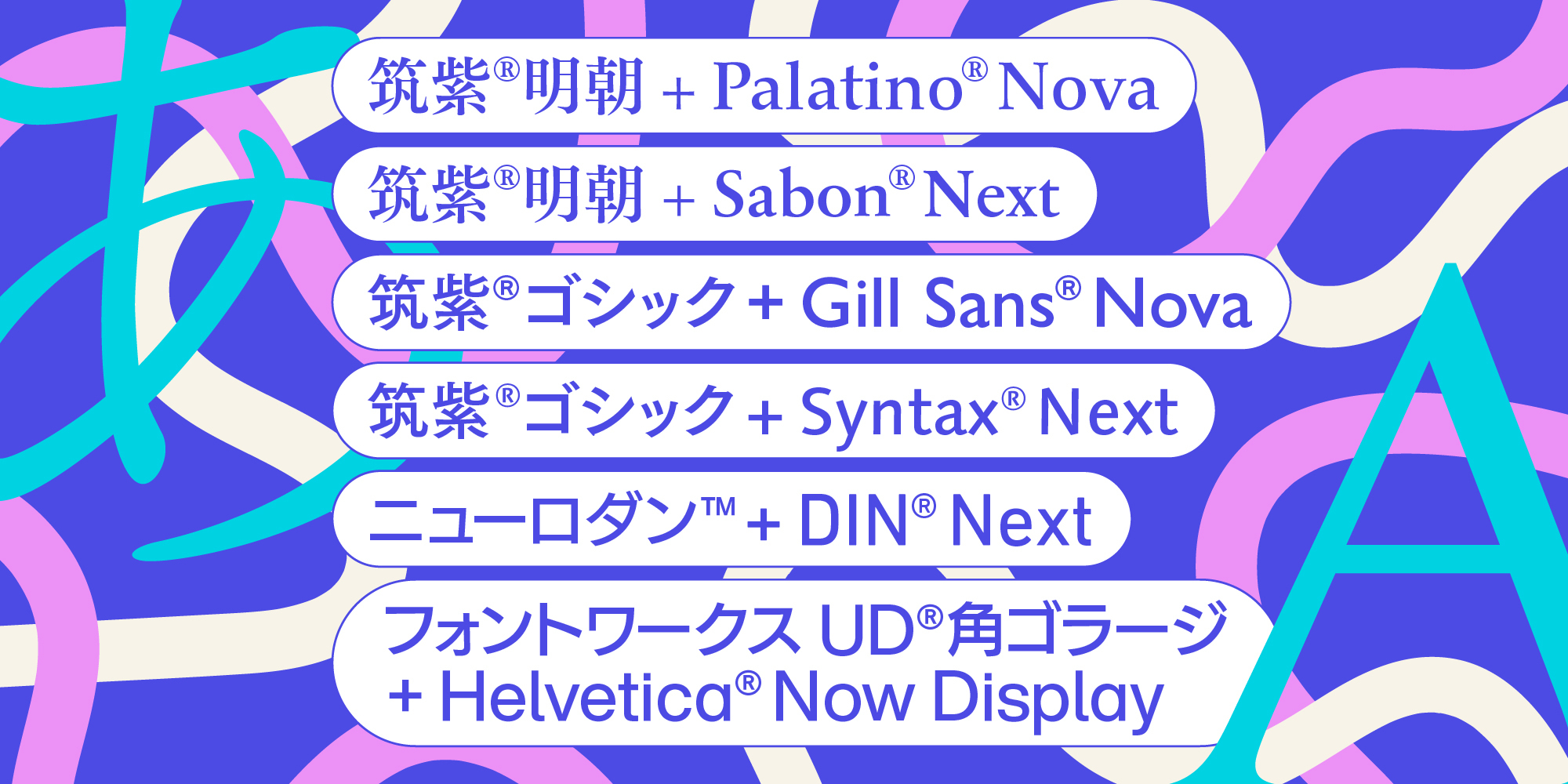
Monotype、人気書体 筑紫書体シリーズやHelvetica Nowなどを組み合わせた和欧混植フォント6ファミリーをMonotype Fontsからリリース
Monotypeが提案する、美しく心地よい和欧混植フォント
和欧混植とは、日本語の文字(和文書体)とアルファベットなどのラテン文字と数字(欧文書体)を組み合わせた文字組版のことです。デザインやレイアウト上の調整を行い、違和感なく両方の文字体系を組み合わせることで、より美しく読み心地のよい文字の表現が可能になりました。
今回、Monotypeを代表する和文・欧文書体である、筑紫®ゴシック、筑紫®明朝、フォントワークス UD®角ゴ_ラージ、ニューロダン™、Gill Sans® Nova、Helvetica® Now Display、Palatino® Nova、DIN® Next、Syntax® Next、Sabon® Nextを組み合わせました。
本書体は、Monotypeと筑紫書体シリーズなどで知られるFontworks®がひとつになったことをきっかけに、よりフォントの持つ可能性を広げることを目指して誕生した新しいコンセプトのフォントです。欧文と和文のデザインを一体化させたことで、文化や言語の枠を越えた自然な調和を実現しています。このフォントは、デザイン性だけでなく、ユーザーの創造性を最大限に引き出すために柔軟に対応できる強固な基盤を提供します。
和欧混植フォント一覧
| 筑紫明朝+Palatino Nova | 7ウェイト |
| 筑紫明朝+Sabon Next | 7ウェイト |
| 筑紫ゴシック+Gill Sans Nova | 8ウェイト |
| 筑紫ゴシック+Syntax Next | 8ウェイト |
| ニューロダン+DIN Next | 6ウェイト |
| フォントワークスUD角ゴラージ+Helvetica Now Display | 8ウェイト |
【Monotype和欧混植フォントの特長】
・厳選した書体の組み合わせと、混植時の美しさ
Monotypeの和欧混植フォントは、数ある和文・欧文書体から組み合わせを厳選。それぞれの持つ個性や美しさを活かし、可読性が高く洗練された印象を実現しました。
また混植時の見え方の美しさにもこだわりました。洗練された欧文書体が和文中に入ることで、全体が引き締まります。特に数字は使用頻度が高いため、本書体を使用することで読みやすさや美しさがより際立ちます。
多様化するコミュニケーションのニーズやグローバルな視点でのフォント活用が求められる中、和欧混植フォントは多様な場面での使用を可能にし、コミュニケーションをより豊かで魅力的なものにするために開発されました。これにより、広告、映像、ウェブデザインなどの幅広い分野で新しい表現を追求するクリエイターたちにとって、欠かせないツールとなることを目指しています。
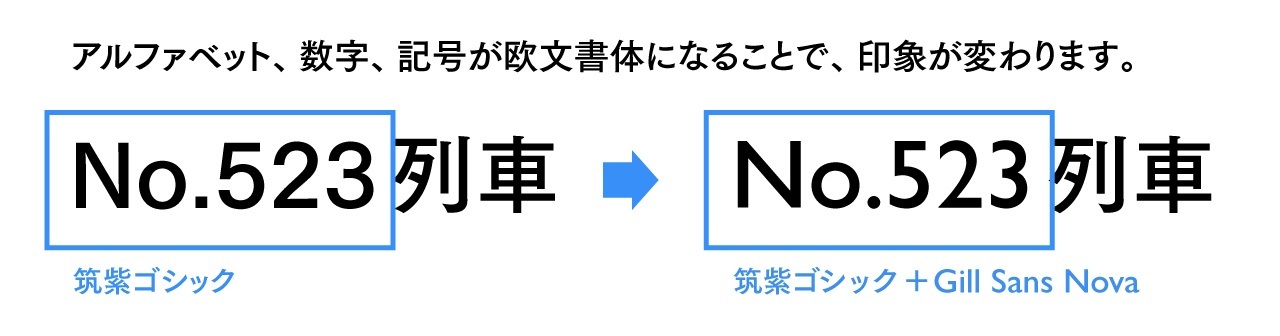
・特別なソフトや知識は不要
和文と欧文の混植は、デザインツールのレイアウト機能を利用し、専門知識も必要でした。和欧混植フォントを利用することにより、特別なソフトや知識がなくても、誰にでも手軽に美しい文字表現が可能になります。
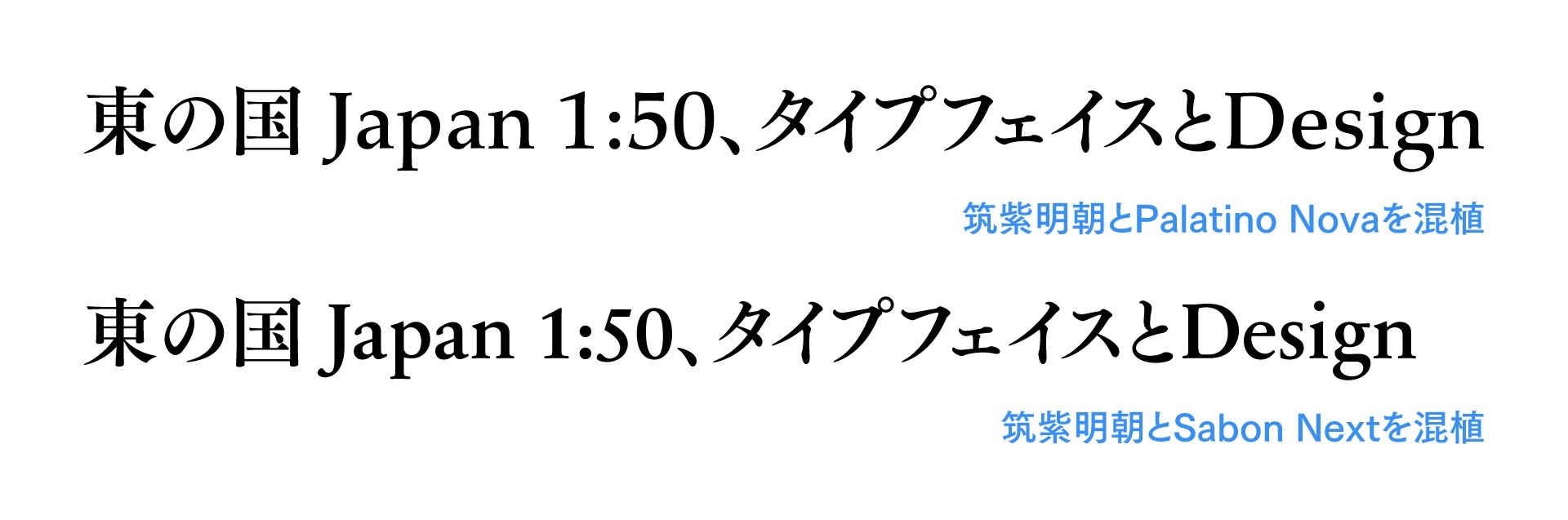
提供を開始する6書体
Monotypeを代表する和文・欧文書体から、6つの組み合わせが生まれました。組み合わせごとに複数のウェイトとイタリック*もご用意しています。
筑紫明朝+Palatino Nova(7ウェイト)
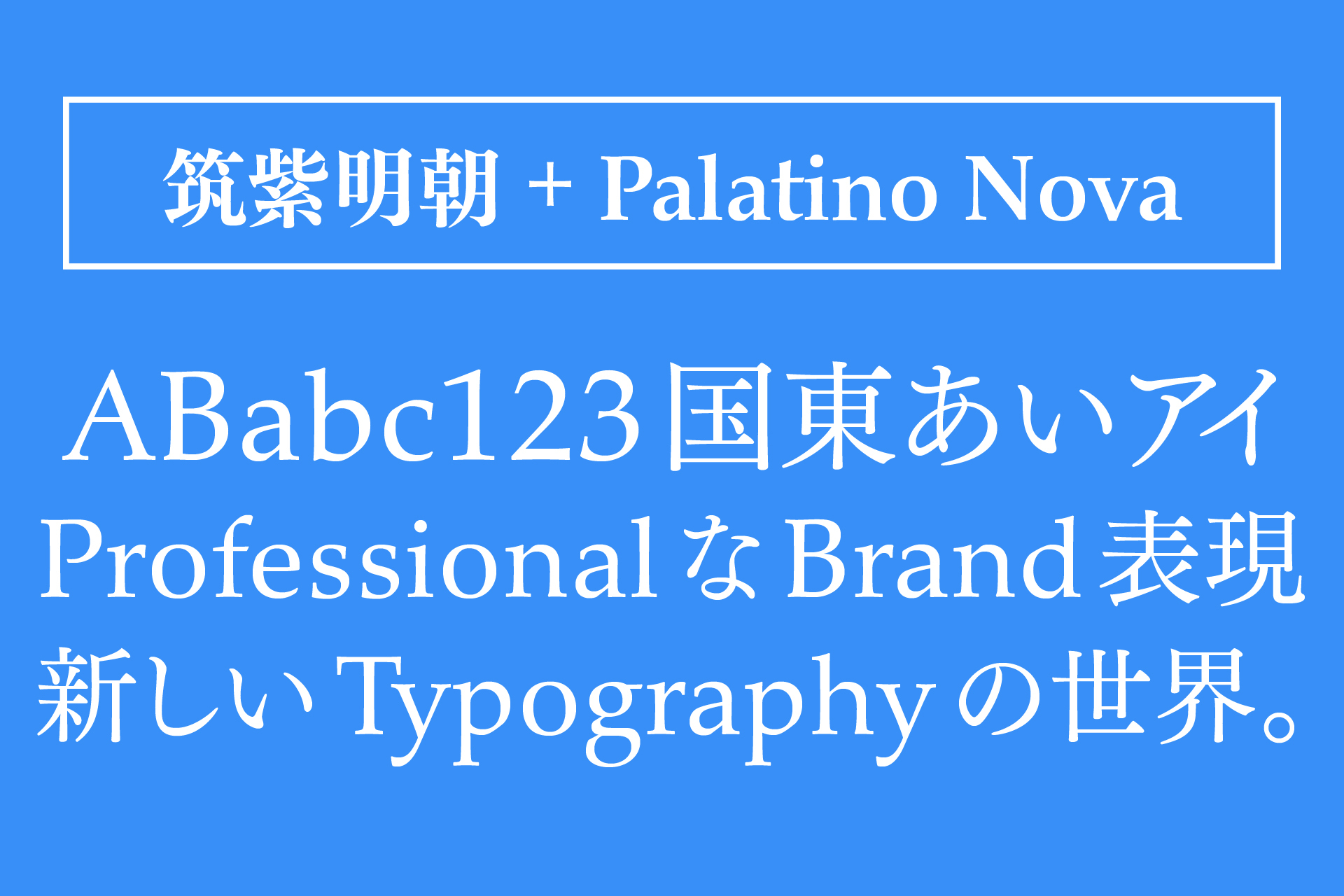
活字・写植時代の本質を踏襲し、明朝体とはどうあるべきかを最大限に考慮した筑紫明朝と、書籍の本⽂・⾒出しを問わず、そして時代に左右されず使われ続けているセリフ書体Palatinoの改刻・ウェイト拡張版Palatino Novaを組み合わせました。
柔らかさや伝統を感じる混植で、長文で使用しても読みやすく、印象に残る言葉を大きく表示することにも適しています。
筑紫明朝+Sabon Next(7ウェイト)
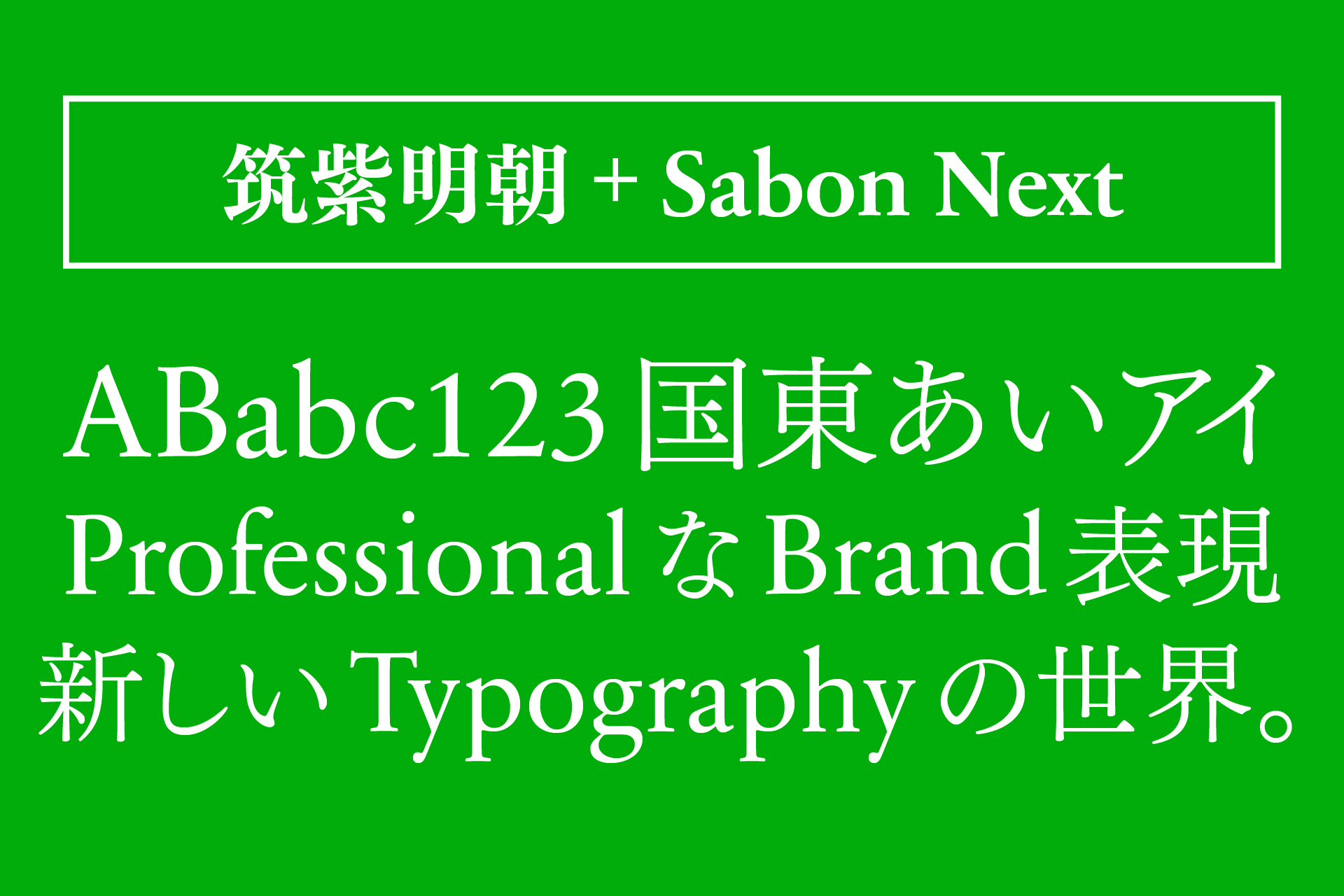
活字・写植時代の本質を踏襲し、明朝体とはどうあるべきかを最大限に考慮した本文用書体 筑紫明朝と、書籍の本⽂、⾒出しを問わず、しかも時代に左右されず使われ続けているセリフ書体Sabonの改刻・ウェイト拡張版Sabon Nextを組み合わせました。
伝統的でエレガントな印象を生み出す組み合わせで、品格や華やかさを感じさせたい場面に適しています。
筑紫ゴシック+Gill Sans Nova(8ウェイト)
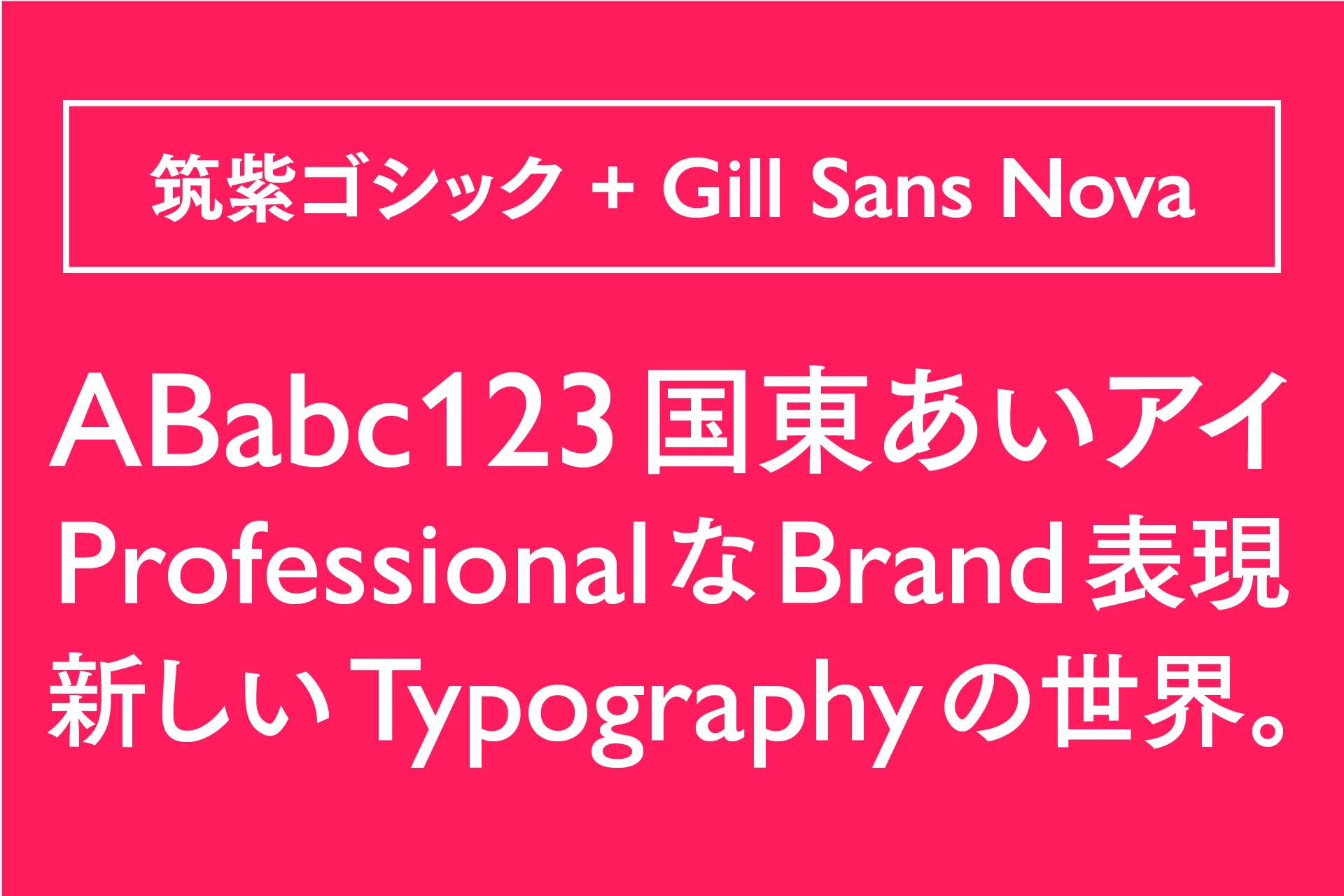
現代のシャープさやクリーンな硬質さと、クラシックな味わいや柔らかな部分を融合させた筑紫ゴシックと、伝統や格調を演出したい場合に使われるヒューマニスト・サンセリフ体の先駆的書体Gill Sansの改刻・ウェイト拡張版Gill Sans Novaを組み合わせました。
可読性に優れ、信頼感や伝統の中にも柔らかい印象を感じさせたい場面に適しています。
筑紫ゴシック+Syntax Next(8ウェイト)
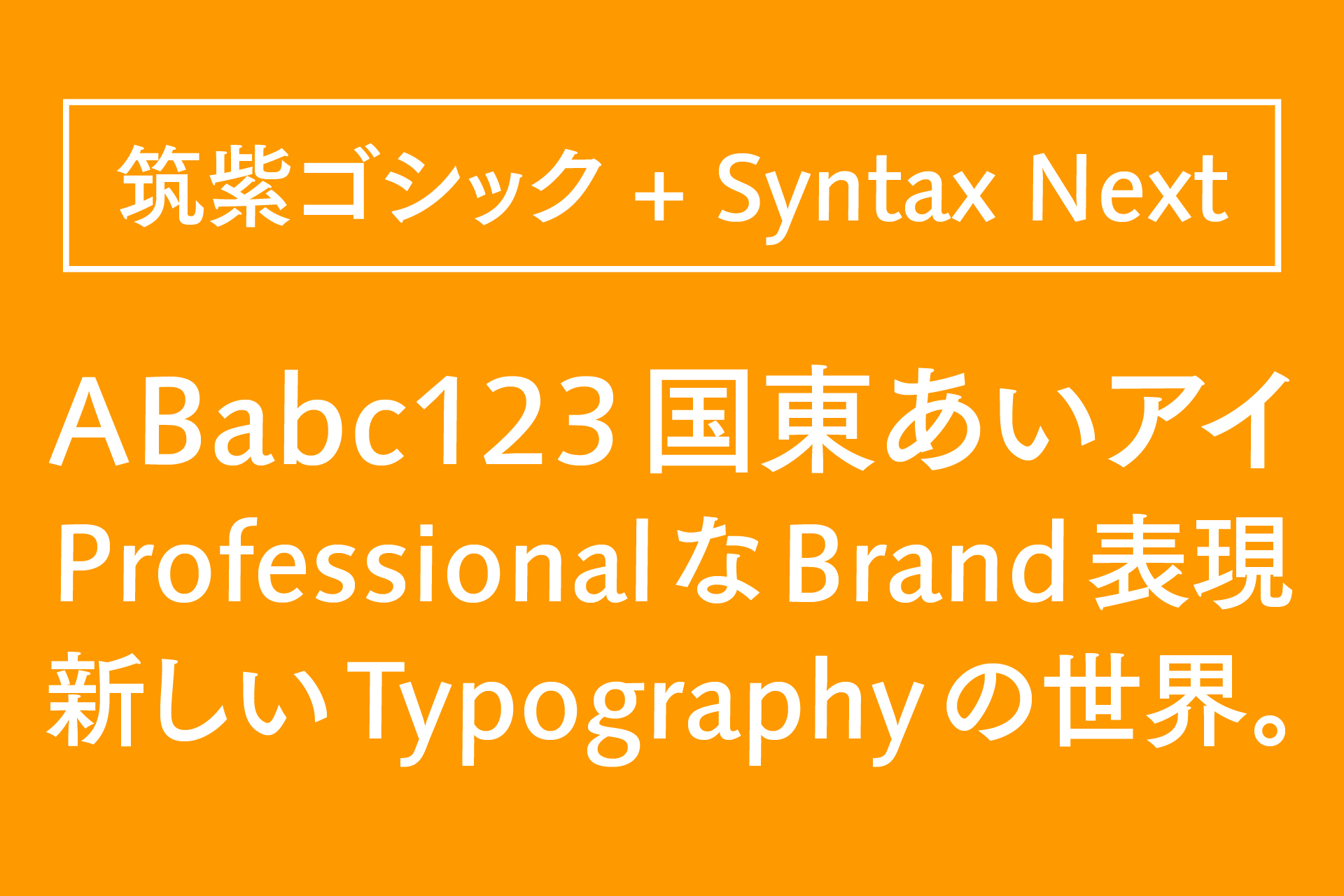
現代のシャープさやクリーンな硬質さと、クラシックな味わいや柔らかな部分を融合させた筑紫ゴシックと、ヒューマニスト・サンセリフ体ではFrutiger®と並んで評価される書体Syntaxの改刻・ウェイト拡張版Syntax Nextを組み合わせました。
明るさと読みやすさの中に、現代的で洗練された印象のある混植です。本文からデジタルデバイスまで幅広く活用できます。
ニューロダン+DIN Next(6ウェイト)
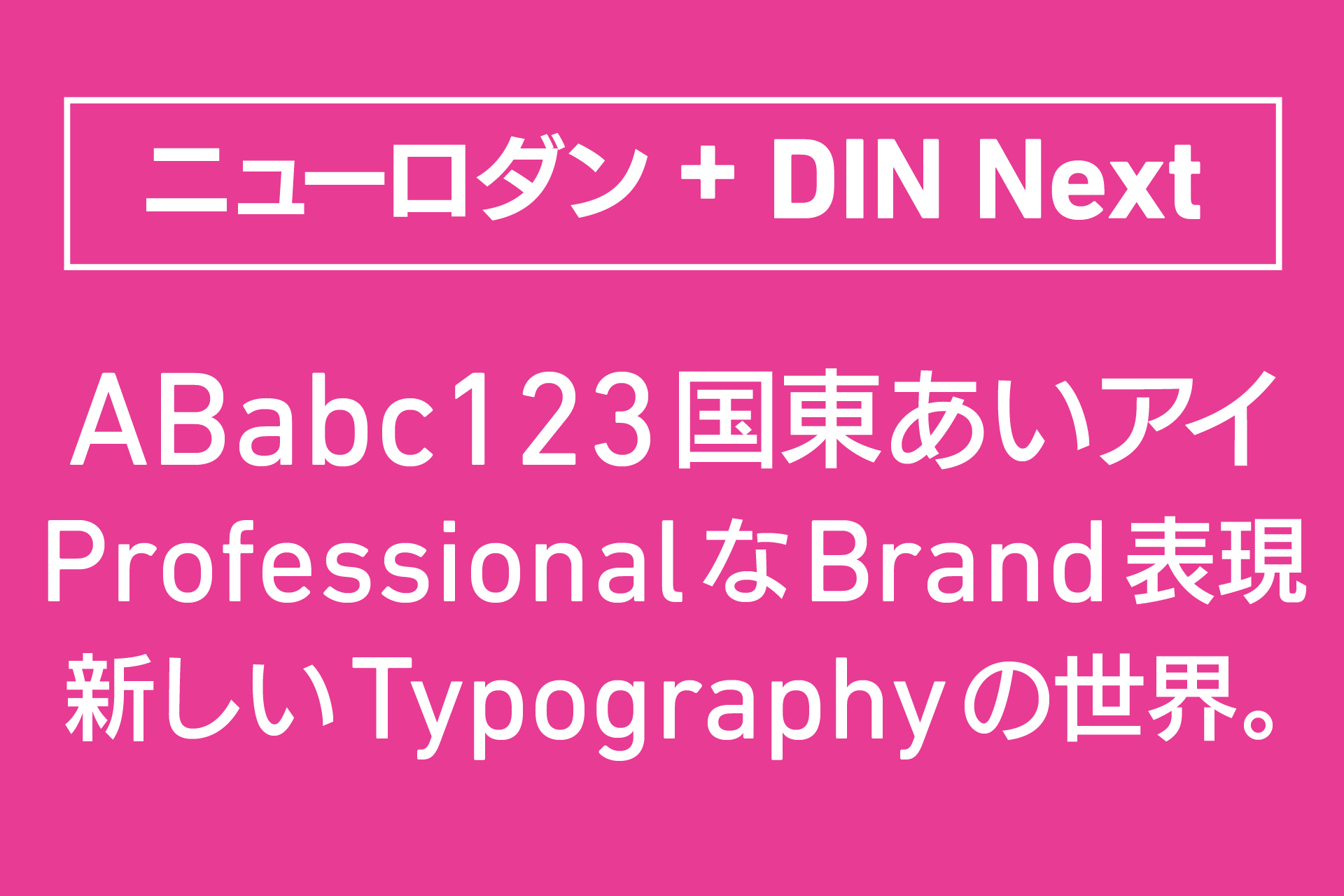
フォントワークスのゴシック体ニューロダンとドイツの工業用規格から生まれたDIN 1451をベースに、現代的なサンセリフ書体DIN Nextを組み合わせました。
機能的でシンプルな印象のある混植で、小さい文字でも読みやすく機能的です。
フォントワークス UD角ゴ_ラージ+Helvetica Now Display(8ウェイト)
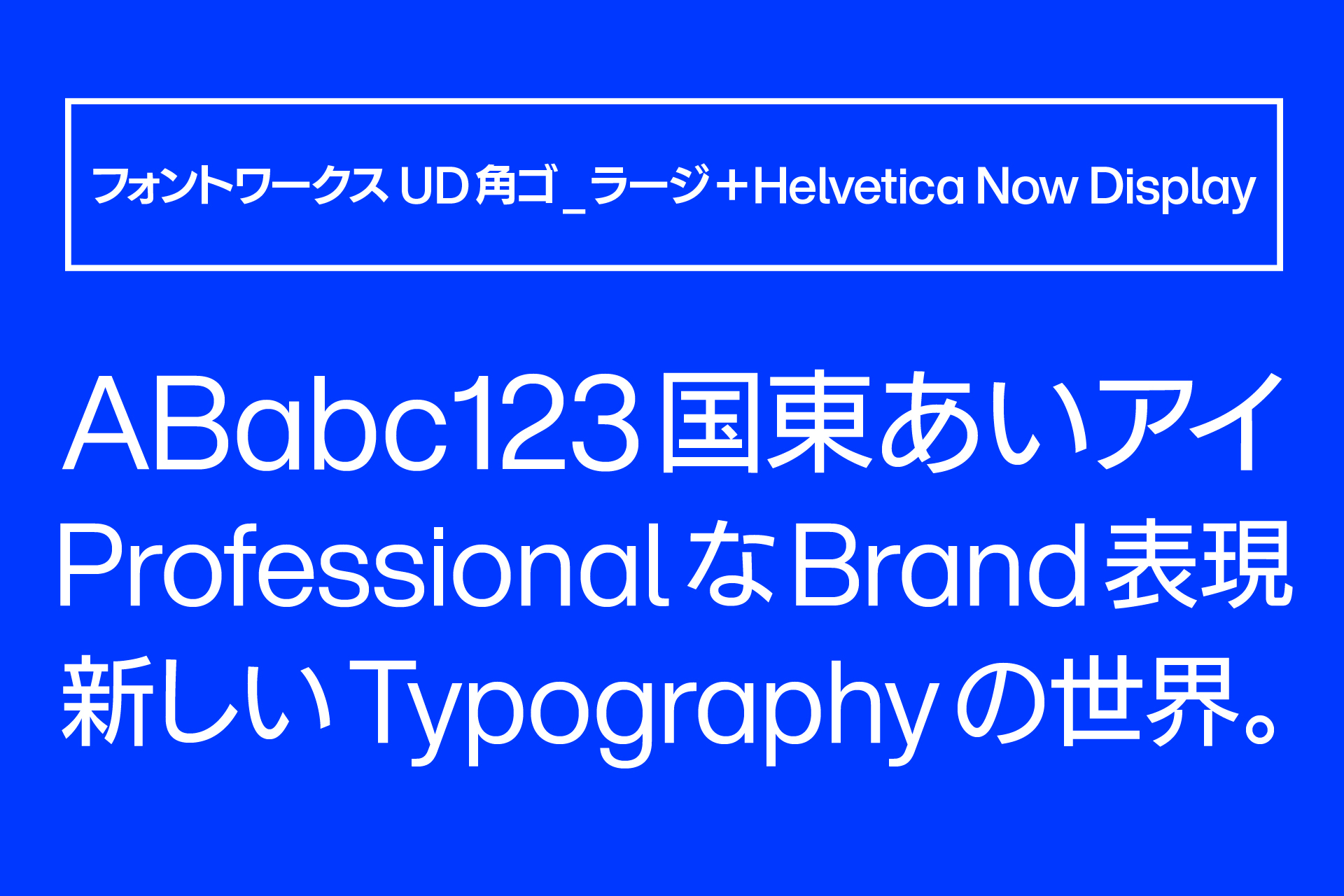
見出しに最適なモダンゴシック体 ニューロダンをベースにしたフォントワークス UD角ゴ_ラージと、現代のブランディングの課題を解決する書体として誕生したHelvetica Nowのうち、大きな見出し用に字間が調整されているDisplayを組み合わせました。
明瞭で伝わりやすい組み合わせで、サインや見出し、機能説明などに適しています。
MonotypeとFontworksが協力して、両社の強みを最大限に活かした混植フォントを全世界に向けて発表します。 情報の多言語化の時代の要求に応えるため、Fontworksの和文書体にサイズや位置を合わせた欧文書体を組み込みました。 日本語と西欧の言語を混植する際に、これまでの和文従属欧文とは違った世界レベルの品質を提供できることを嬉しく思います。
写植時代以後、和文を作るデザイナーの多くは付属の英数字をデザインする際、CenturyやHelvetica等オリジナルを使うことはできず、それらに似たイメージでデザインする必要がありました。
MonotypeとFontworksが1つになったことで、これら欧文が和文字用に調整と組み合わせが可能になりました。 「真の和文フォント」として、世界に発信できるものになるでしょう。